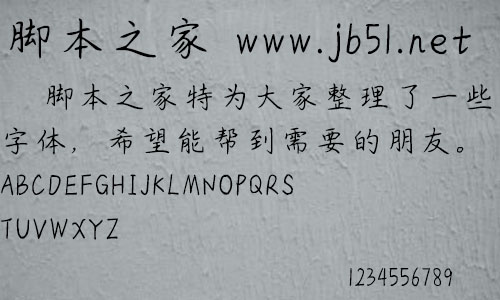
漢儀晚安讀做我愛(ài)你簡(jiǎn)一款不錯(cuò)的藝術(shù)字體,由漢儀字庫(kù)出品,字體筆觸纖細(xì),字形端正,適合應(yīng)用于藝術(shù)設(shè)計(jì)、平面宣傳設(shè)計(jì)、網(wǎng)頁(yè)設(shè)計(jì),書(shū)法字帖等領(lǐng)域,需要的朋友可以前來(lái)本站下載。